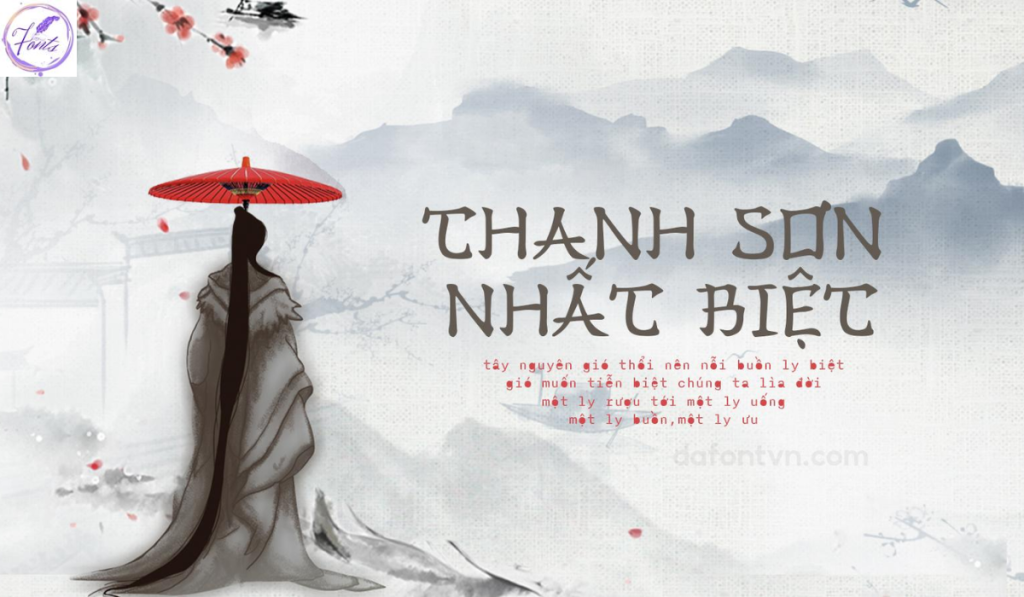
Top 10 font chữ cổ trang việt hóa đẹp 2024
Khi nói đến việc tái hiện không khí của quá khứ, không có gì tốt hơn việc sử dụng font chữ cổ trang việt hóa. Những thiết kế này không chỉ giúp chuyển tải nét đẹp của văn hóa Việt Nam xưa mà còn mang lại một hơi thở mới cho các tác phẩm hiện đại. Font chữ cổ trang việt hóa được tạo ra với mục đích phục vụ cho các dự án có yếu tố lịch sử, văn hóa truyền thống, từ sách, báo, tạp chí đến các thiết kế website và marketing.
Top 10 font chữ cổ trang việt hóa đẹp 2024
Font chữ cổ trang thư pháp Ả Rập – Font Kabyah
Font Kabyah là một font chữ cổ trang thư pháp Ả Rập, mang đến vẻ đẹp tinh tế và độc đáo trong thiết kế. Font này được thiết kế để phù hợp với các tác phẩm mang đậm bản sắc văn hóa Ả Rập.
Font chữ cổ trang gothic – Font Despair
Font chữ Despair là một kiểu chữ gothic độc đáo, mang đến cảm giác u ám và bí ẩn. Thiết kế của nó phù hợp cho các dự án nghệ thuật, đặc biệt trong lĩnh vực văn học và điện ảnh. Font này được phát hành vào năm 2020, mang đến cho người dùng một trải nghiệm thị giác mới mẻ với các ký tự sắc nét và phong cách cổ điển, phù hợp với các chủ đề tối tăm và huyền bí.
Font cổ trang Hàn Quốc – Font A Annyeong Haseyo việt hóa
Font việt hóa A Annyeong Haseyo là một font chữ cổ trang lấy cảm hứng từ các ký tự Hàn Quốc, với các nét chữ đẹp mắt và cân đối, phù hợp để sử dụng trong các thiết kế như cổ trang, thư pháp, bìa truyện… Font này mang lại cảm giác cổ điển và trang nghiêm, thường được sử dụng để tái hiện văn hóa, lịch sử và truyền thống qua các tài liệu, biểu đồ hoặc trong nghệ thuật thiết kế đồ họa.
Font chữ cổ trang có chân – Font Daybreaker việt hóa
Font chữ cổ trang Daybreaker là một kiểu chữ được việt hóa hoàn toàn, mang đến sự tinh tế và vẻ đẹp cổ điển cho các thiết kế. Với những nét vẽ độc đáo, font này phù hợp cho các dự án liên quan đến văn hóa và lịch sử. Ngày phát hành của font là 15/07/2023, và nó được tối ưu hóa để hoàn thiện mọi chi tiết.
Font chữ cổ trang việt hóa nét mảnh – Font TLM Take
Font chữ cổ trang TLM Take mang đến vẻ đẹp tinh tế với nét mảnh, phù hợp cho các thiết kế mang phong cách cổ điển. Được Việt hóa bởi Phongchuviet, font này ra mắt vào ngày 08/04/2022, với các ký tự thường và in hoa, giúp người dùng sáng tạo nhiều tác phẩm độc đáo. Font chữ này rất lý tưởng cho các dự án thiết kế nghệ thuật.
Font chữ cổ trang thư pháp – Font MTD Acryle Script
Font chữ cổ trang thư pháp MTD Acryle Script là một trong những font chữ Script Việt hóa đẹp và độc đáo của bộ 410 font MTD do Mộc Hạ Việt hóa. Font chữ này mang phong cách thư pháp cổ điển, phù hợp để tạo typography cho các thiết kế có chủ đề cổ trang, hoài cổ. MTD Acryle Script hỗ trợ tiếng Việt đầy đủ và tương thích với bộ gõ Unikey, Vietkey.
Font chữ cổ trang Trung Quốc – Font SVN Konfuciuz
Font chữ cổ trang Trung Quốc SVN Konfuciuz là một kiểu chữ mang đậm nét văn hóa cổ điển, được thiết kế bởi tác giả TMT. Font này được sử dụng rộng rãi trong các dự án thiết kế liên quan đến văn hóa và lịch sử, tạo cảm giác trang nghiêm và độc đáo. Font SVN Konfuciuz đã được phát hành gần đây, phục vụ nhu cầu của những người yêu thích nghệ thuật chữ viết cổ trang.
Font chữ cổ trang Nhật Bản – Font KZ Bladerunner
Font chữ cổ trang KZ Bladerunner Việt Hóa là kiểu font chữ Nhật Bản độc đáo, phù hợp với các thiết kế mang phong cách cổ điển và truyền thống. Đã được Việt Hóa hoàn chỉnh, font này mang đến sự linh hoạt và đa dạng trong việc sáng tạo nội dung. Với đặc điểm nét vẽ cổ điển và trang nghiêm, KZ Bladerunner Việt Hóa là lựa chọn lý tưởng để tạo điểm nhấn độc đáo trong các dự án thiết kế.
Font chữ cổ trang đơn giản – Font Designors
Font chữ cổ trang đơn giản – Font Designors là một phông chữ độc đáo, mang phong cách cổ điển và thanh lịch. Với các nét chữ tinh tế và đường cong mềm mại, font này mang lại cảm giác cổ xưa nhưng vẫn hiện đại. Phù hợp cho các dự án thiết kế, in ấn và trang trí có chủ đề cổ trang.
Font cổ trang viết tay – Font Absolute
Font Absolute là một phông chữ cổ trang Việt hóa, nổi bật với các nét chữ mềm mại và tinh tế, phù hợp cho thiết kế mang đậm phong cách truyền thống. Font này đã được Việt hóa tỉ mỉ, bao gồm các dấu câu được thiết kế đẹp mắt, giúp tạo nên sự hài hòa trong các tác phẩm nghệ thuật.